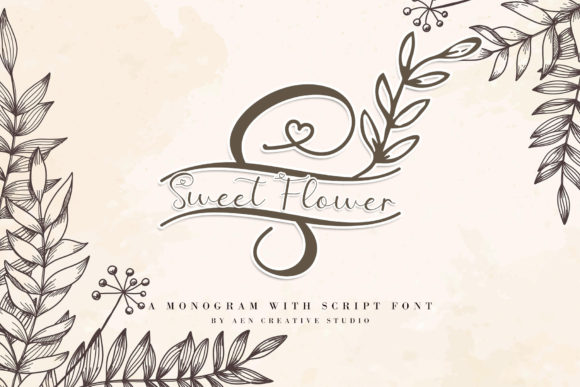
Sweet Flower Monogram
適切なデザイン要素を見つけるのは難しい場合がありますが、Sweet Flower Monogramは作品を即座に引き立てる優れたコレクションを提供します。
POD(オンデマンド印刷)製品、結婚式の招待状、またはソーシャルメディアのグラフィックを作成している場合でも、Sweet Flower Monogramは理想的です。